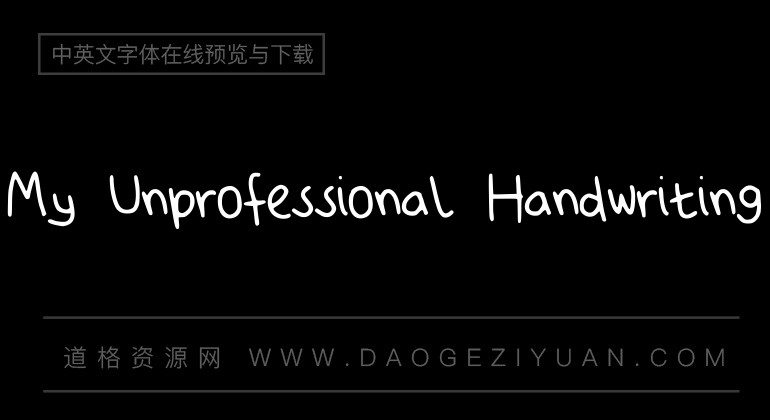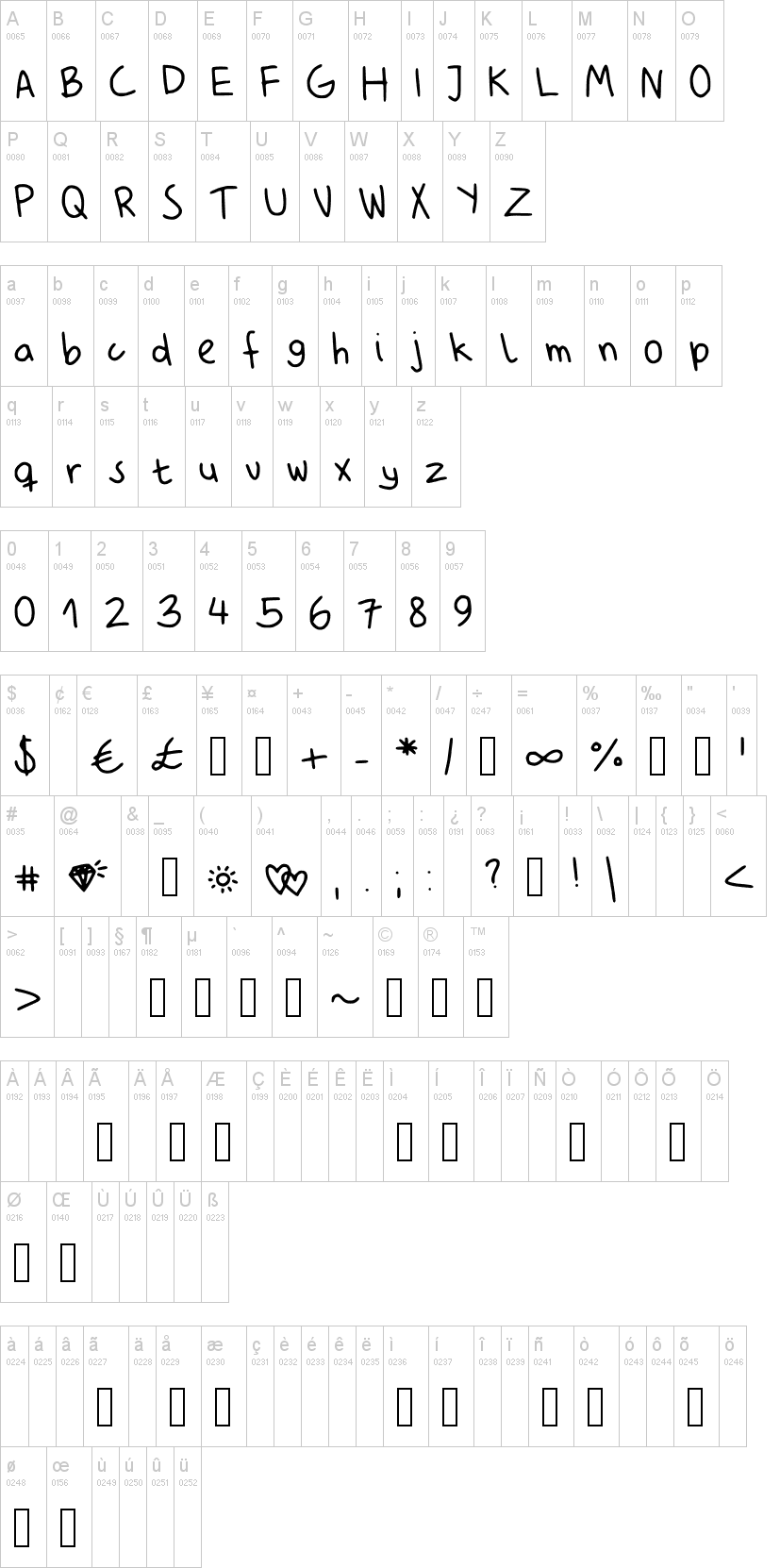
My Unprofessional Handwriting
My Unprofessional Handwriting 字体是一款手写字体,它采用了自然的手写风格,让您的文字更加真实自然。它的字体特点是比较粗糙,而且有一种不专业的感觉,让您的文字更加有个性。它还具有可定制的功能,您可以根据自己的需求来调整字体的样式和大小,让您的文字更加独特。
My Unprofessional Handwriting是一款非常不错的手写艺术字体,具有很好的视觉感,适合于文化类的宣传设计、商业类品牌的广告和产品包装设计以及个性化文字排版等较多场景。
My Unprofessional Handwriting字符映射图